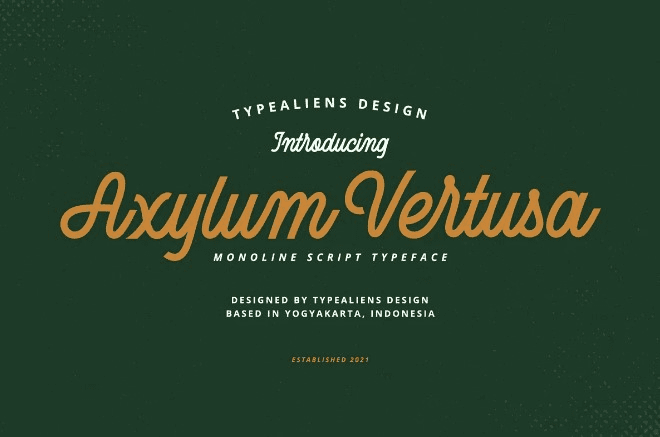
[Creativemarket] Axylum Vertusa Font
Название: Axylum Vertusa Font
[Creativemarket] Axylum Vertusa Font
Axylum Vertusa - это чистый монолинный шрифт, потому что он современный, этот шрифт идеально подходит для дизайна социальных сетей, логотипов и т.д.